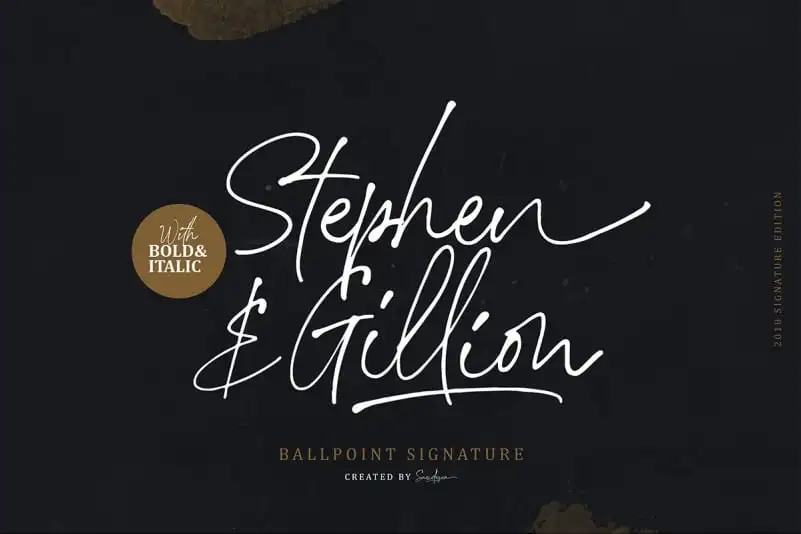
Stephen Gillion Script Font – Download Grátis
A Stephen Gillion Script Font é uma delícia para quem busca uma fonte que se destaca por seu estilo autêntico e artesanal. Inspirada na assinatura única de um designer, ela apresenta caracteres decorativos e uma linha de fundo dançante. Esta fonte foi criada pela Saridezra e compartilhada em 99designs, projetada para criar logotipos de marca, designs de roupas bonitos ou até mesmo convites de casamento sofisticados, com suas citações escritas a mão. Mas o que realmente faz esta fonte ser uma experiência única é seu coração-shaped connector. Essa característica especial e exclusiva adiciona um toque de personalização e amor ao design. Além disso, ela já vem PUA Encoded, facilitando sua utilização em qualquer sistema ou plataforma digital. Se você está procurando por uma fonte que expressa sua individualidade e elegância através do estilo autoral, a Stephen Gillion Script Font é definitivamente o tipo de arte que você precisa.